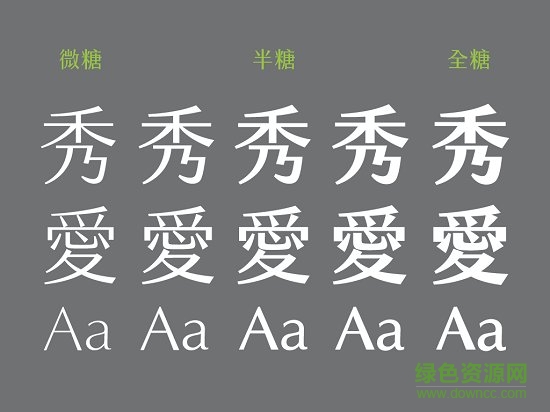
金萱體是臺(tái)灣眾籌的常用字體,打造最本土最正宗的臺(tái)灣字體,國(guó)字國(guó)造,讓廣大民眾都可以享受到本字體的設(shè)計(jì)成果,讓大家的廣告策劃字體選擇更加自由!
「金萱」是道地的臺(tái)灣茶,所以在創(chuàng)作這套字型時(shí),我們特別設(shè)計(jì)了茶文化有趣的icon,例如金萱奶奶、手搖杯、茶壺等可愛(ài)元素,也致敬臺(tái)灣特有的手搖攤文化。
金萱融入更趣味的元素,字重的命名以「手搖攤系統(tǒng)」:「二分糖、微糖、四分糖、半糖、八分糖」,能夠一眼看出粗細(xì)級(jí)距差異,也更能感受到字型應(yīng)用的樂(lè)趣。
金萱是一套風(fēng)格介于明體與黑體之間的字型,被定位在「第二基本書體」,融合了黑體的理性與明體的感性,泛用性非常高。就算是擔(dān)綱短篇內(nèi)文的角色,也能適得其所;而作為「展示字型」,也能在大多情況適用──怎么搭,都加分,就像是衣柜里那條百搭的卡其褲。
從概念、質(zhì)量控管、筆畫造型、空間比例、中英數(shù)字與各式符號(hào),都由justfont打造。是相當(dāng)難得的臺(tái)灣本土自產(chǎn)字型。爽朗的撇捺、圓潤(rùn)中帶力度的勾筆中,散發(fā)臺(tái)灣的親切氣息。我們期望以「金萱」栽培出新鮮的臺(tái)灣文字風(fēng)景。
有趣的特色:命名、手搖攤系統(tǒng)與符號(hào)
之所以會(huì)取名為金萱,一方面是因?yàn)檫@個(gè)字體「混合」的特征(金萱是發(fā)酵程度介在中間偏未發(fā)酵的茶種);另一方面,筆形硬朗,符合「金」的印象;粗細(xì)對(duì)比的張力中,又產(chǎn)生優(yōu)雅的韻味,聯(lián)想到「萱」的茶香氣。
另外,字型檔案不只有文字,還有許多有趣的排版規(guī)劃,例如「字體系列」與各種各樣的圖案符號(hào)。正因?yàn)椤附疠妗故堑氐赖呐_(tái)灣茶,所以在創(chuàng)作各種字型檔案特征時(shí),我們也想融合,甚至致敬臺(tái)灣特有的手搖攤文化。
筆畫造型
若希望強(qiáng)調(diào)漢字韻味,也需要在筆畫造型上琢磨。金萱的撇、捺、挑、點(diǎn)比較硬朗,曲線彎曲程度較不圓滑,帶出筆畫的力道,筆畫尾端切線角度也務(wù)求干凈利落。點(diǎn)相對(duì)其他字型比較大,在小字時(shí)也能帶出視覺(jué)張力;勾筆是最有特色的部件,相對(duì)比較剛硬的筆畫,它顯得特別圓滑,適當(dāng)中和了剛強(qiáng)的氣息,爽朗中點(diǎn)綴出帶有親切感的樣貌
骨架
金萱的架構(gòu)是瘦長(zhǎng)的,「中宮」相較同類型字體,也比較緊收,重心也更偏上。相較日系的明黑混合書體而言,金萱在骨骼上比較重視內(nèi)斂、緊實(shí)的視覺(jué)效果。這個(gè)概念落實(shí)到每個(gè)字上面,在排印時(shí)會(huì)帶出更濃厚的漢字韻味。